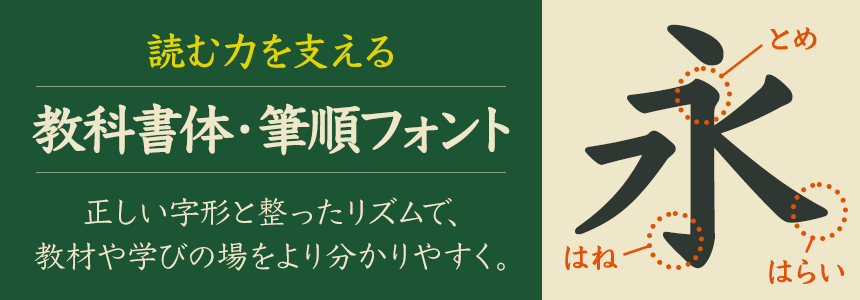
気になるフォント「教科書体」
今回ご紹介するのは『教科書体・学参書体』です。
新入学生を迎える時期になると、この教科書体を使って授業用のプリントを作ったり、入学時期過ぎたころからお問い合わせが多くなる書体です。
教科書体とは「小学校の教科書で使われる筆書きの楷書体に近いもの」となっていて、文部省の学習指導要領で提示されている字体です。
まずは通常の明朝体と「教科書体」で文字の比較をしてみました。
こうやって並べてみると、文字の懐・大きさが明朝は枠いっぱいに作られているのに対して、教科書体は余裕がある作り(小さめ)に見えます。
「はね」や「押さえ」「とめ」などもよく見ると、より慣れしたしんだ筆記体に近いのは教科書体だと感じます。
・DF教科書体
【エヌアイシィ】
・JTCナミキ教科書体
・JTCナミキかきじゅん1 書き順を教えてくれるフォントです。※小学1・2年生で覚える「かな」と「漢字」
・JTCナミキかきじゅん2 ※小学3・4年生で覚える「漢字」
・JTCナミキかきじゅん3 ※小学5・6年生で覚える「漢字」
【イワタ】
・イワタ筆順フォント新教科書体 B
【シーアンドジイ】
・AR教科書体
【モトヤ】
・モトヤ教科書
【フォントワークス】
・ユトリロ ※ぽくない名前ですが、こちらも教科書体です